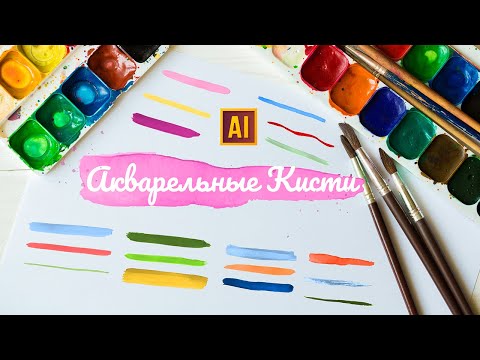
Как создать эффект мазка кисти с помощью шрифта
Узнайте, как создать на странице видовой эффект, напоминающий свежее написание мазка кисти. Использование различных шрифтов и их адаптация сделают ваш контент более креативным и привлекательным.
Выбирайте шрифты с насыщенными и разнообразными перьями, чтобы создать вид мазка кисти. Некоторые шрифты специально созданы для имитации почерка.
Используйте различные вариации размера и наклонности шрифта, чтобы подчеркнуть эффект мазка кисти. Играйте с плотностью шрифта, чтобы создать динамический образ.
Комбинируйте разные шрифты и стили текста, чтобы добавить глубину и ощущение реального мазка кисти. Экспериментируйте с цветами и прозрачностью, чтобы создать уникальный и эмоциональный контент.